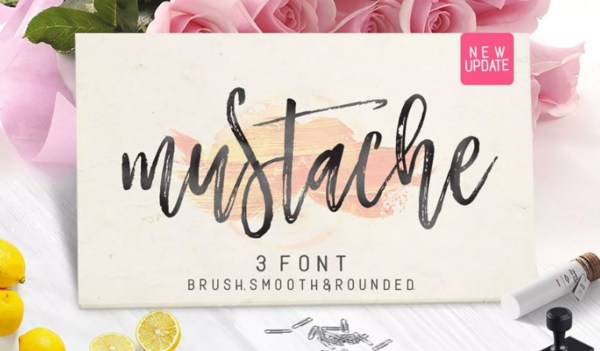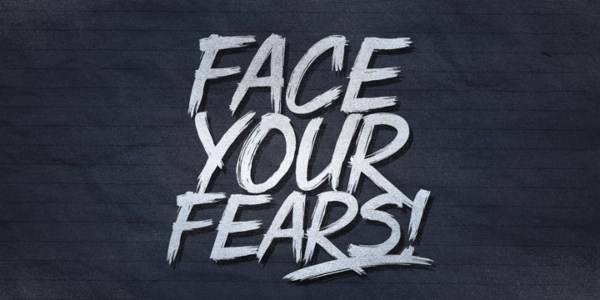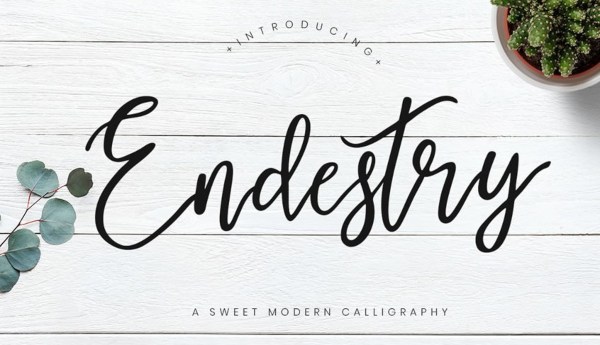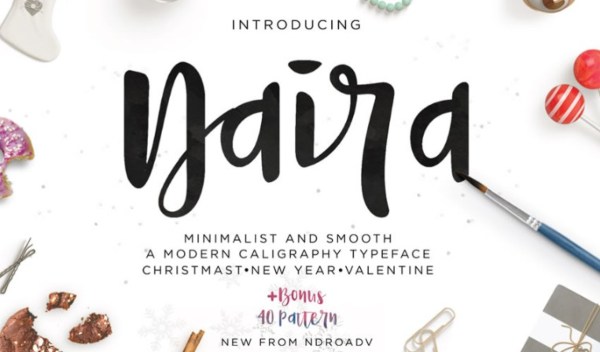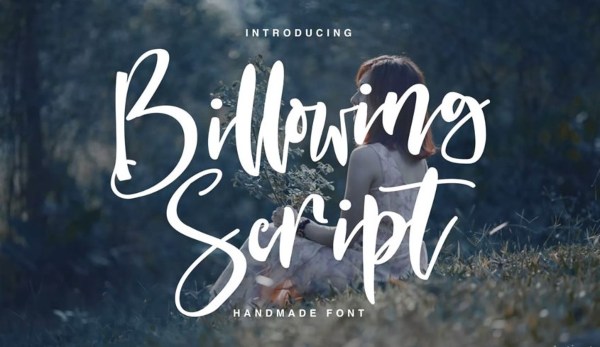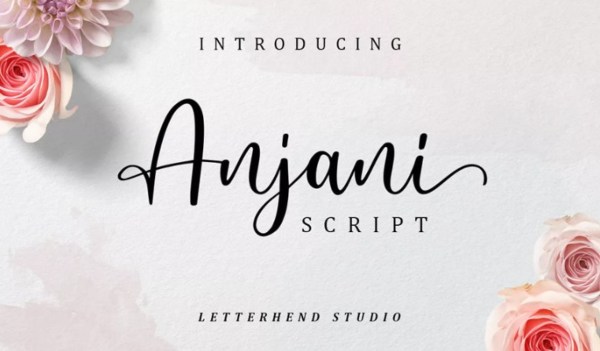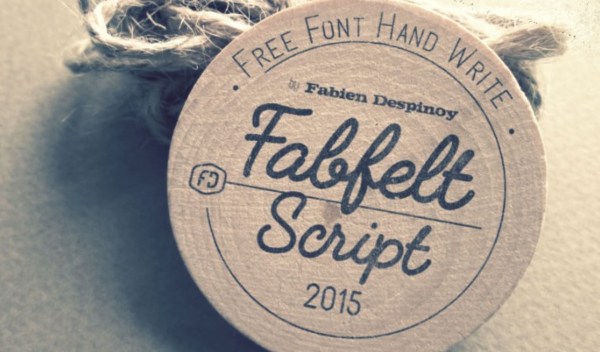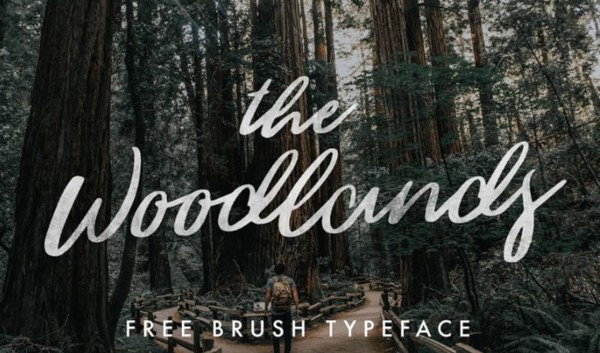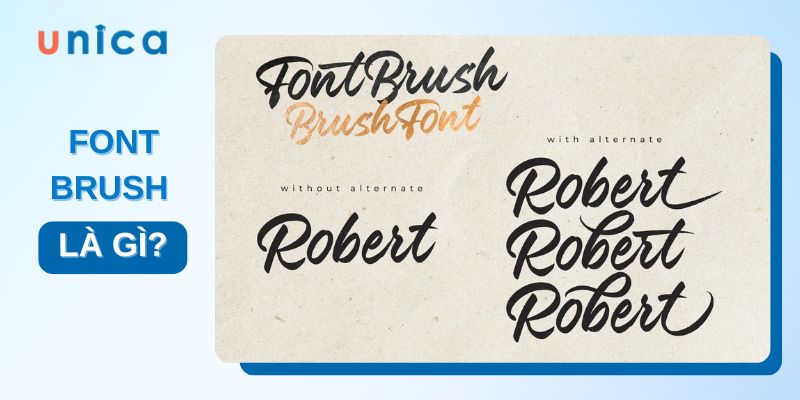
TOP 8 Font brush Việt hóa đẹp được nhiều người yêu thích
Bạn là một Designer mới vào nghề? Bạn đang quan tâm và đi tìm những font chữ Việt hóa đẹp để phục vụ cho công việc thiết kế sáng tạo của mình? Bạn đang không biết nên lựa chọn font chữ viết tay nào? Hãy cùng Unica đi tìm hiểu các font brush Việt hóa (font chữ viết tay) đẹp ngay.
Font Brush là gì?
Font brush là một font chữ được xây dựng thiết kế dưới dạng viết tay hoặc mô phỏng nét viết tay thành dạng vector có thể sử dụng trên các phần mềm hoặc công cụ máy tính, đặc biệt là trong các công cụ thiết kế. Theo thời gian các font chữ được sáng tạo và phát triển một cách rộng rãi,, mạnh mẽ trên toàn cầu, kèm theo đó là nhu cầu sử dụng font chữ brush đẹp của các nhà thiết kế Việt cũng tăng cao, đặt ra yêu cầu làm sao có thể chuyển đổi các font chữ brush của nước ngoài được Việt hóa và tìm đâu những font chữ đó.
Font Brush là gì
Tìm hiểu khái niệm Font Brush
Top 8 Font brush Việt hóa đẹp
Font SVN-DHF Dexsar Brush
Font brush Việt hóa SVN-DHF Dexsar Brush do nhà thiết kế Dexsar Harry Anugrah sáng tạ, là một font chữ cọ vẽ có độ chi tiết khá cao với hơn 240 glyphs. Đồng thời được tích hợp cả tính năng OpenType giúp bạn dễ dàng điều chỉnh theo ý muốn của mình. Font chữ này xuất hiện nhiều trong các loại thiết kế banner, áo phông hoặc thiết kế phục vụ cho mục đích in ấn.
Font brush SVN-DHF Dexsar Brush
Font Endestry Modern Calligraphy
Font chữ Endestry Modern Calligraphy này có đường nét khá mềm mại, uốn lượn rất đẹp rất phù hợp cho các mục đích như tiêu đề thư mời, thiệp mời, hoặc dùng để thiết kế logo cũng rất ấn tượng, phù hợp với các ngành nghề lĩnh vực làm đẹp.
Font Endestry Modern Calligraphy
Font Script đẹp Naira
So với Font chữ Endestry Modern Calligraphy trên thì font chữ Script Naira có nét dày hơn, mềm, đậm và nhiều ký tự sáng tạo khác nhau. Đây cũng là một lựa chọn rất mới mẻ và phù hợp cho các sản phẩm truyền thông hoặc dùng để thiết kế logo/bộ nhận dạng thương hiệu.
Font Script đẹp Naira
Font chữ Billowing Script
Nếu bạn để ý bạn sẽ thấy font chữ Billowing Script (Envato Elements) gần giống với font chữ Naira. Tuy nhiên ngoài tương đồng về nét chữ dày, đậm thì đặc điểm của chữ này cũng có những góc nhọn hơn ở những nét chuyển đổi từ chữ này sang chữ khác, tạo nên sự khác biệt khá rõ ràng và hơi thở năng động vui vẻ hơn. Font chữ này nằm trong Envato Elements một trang web cung cấp font chữ đẹp.
Font chữ Billowing Script (Envato Elements)
Font Anjani Script Modern Calligraphy
Bạn thấy font brush Việt hóa này thế nào? Rất giống font chữ bên trên phải không? Font này nét thanh mảnh hơn, hiện đại và khá lãng mạn. Font chữ này sẽ khá phù hợp với các sản phẩm thiệp mời, thiệp cưới hoặc tiêu đề thư.
Font Anjani Script Modern Calligraphy (Envato Elements)
Font chữ Fabfelt Script Free
Font chữ Fabfelt là một font script đẹp mang hơi thở cổ điển. Font chữ này khá gọn gàng, các nét chữ đều. Được thiết kế bởi Despinoy Fabien, bạn hoàn toàn có thể sử dụng font chữ này  vào mục đích như thiết kế logo hơi hướng cổ điển, thiết kế áo phông hoặc dùng trong các mục đích cá nhân / thương mại nào đó.
Font chữ Fabfelt Script Free
Font Việt hóa Woodlands
Font chữ Woodlands là một Handwriting font Việt hóa đẹp khá ấn tượng và đẹp mắt. Cảm nhận đầu tiên về font chữ này đó là sự khỏe khoắn, gồ ghề nhưng vẫn mang nét mềm mại đặc trưng của chữ viết tay. Font chữ này sẽ rất phù hợp cho các dự án xây dựng và khẳng định thương hiệu doanh nghiệp hoặc giới thiệu sản phẩm liên quan đến môi trường, thiên nhiên. Đặc biệt font chữ này là font chữ free đấy.
Font Việt hóa Woodlands
Font Mustache Brush Script
Brush font Việt hóa Mustache Brush Script (Envato Elements) lần đầu tiên khi nhìn thấy chúng ta sẽ cảm nhận được ngay sự thân thuộc của nét chữ viết tay như chữ thư pháp. Font chữ này cũng rất đa đăng, bạn hoàn toàn có thể sử dụng font này cho thiết kế các sản phẩm in ấn, thiệp mời, thiết kế mang theo phong cách retro, vintage.
Font chữ Mustahe Brush Script (Envato Elements)
Kết luận
Hi vọng rằng với 8 font brush Việt hóa đẹp này bạn đã có được những gợi ý font chữ đẹp và lựa chọn được font chữ phù hợp cho sản phẩm thiết kế của mình. Đây là kiến thức quan trọng để bạn có thể làm chủ được thiết kế một cách nhanh nhất.